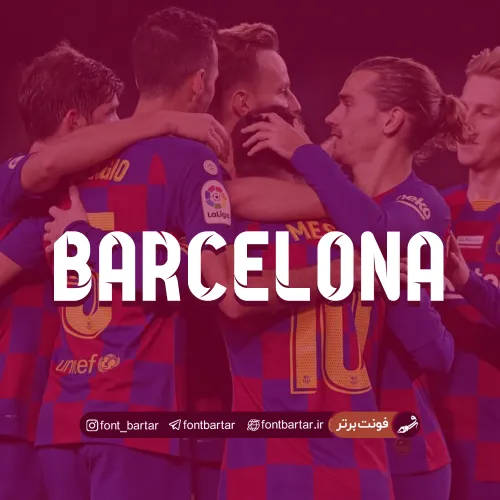
فونت انگلیسی Barcelona
گمان نمی کنیم نیاز به توضیح و معرفی داشته باشد فونت انگلیسی بارسلونا ، این فونت در سال ۲۰۱۳ ، استفاده می شده است و در دسته فونت های مناسب تایپوگرافی محسوب میشود فونت انگلیسی Barcelona هم اکنون به صورت رایگان در فونت برتر در دسترس است لذت ببرید.
فونت Barcelona مورد استفاده برای: